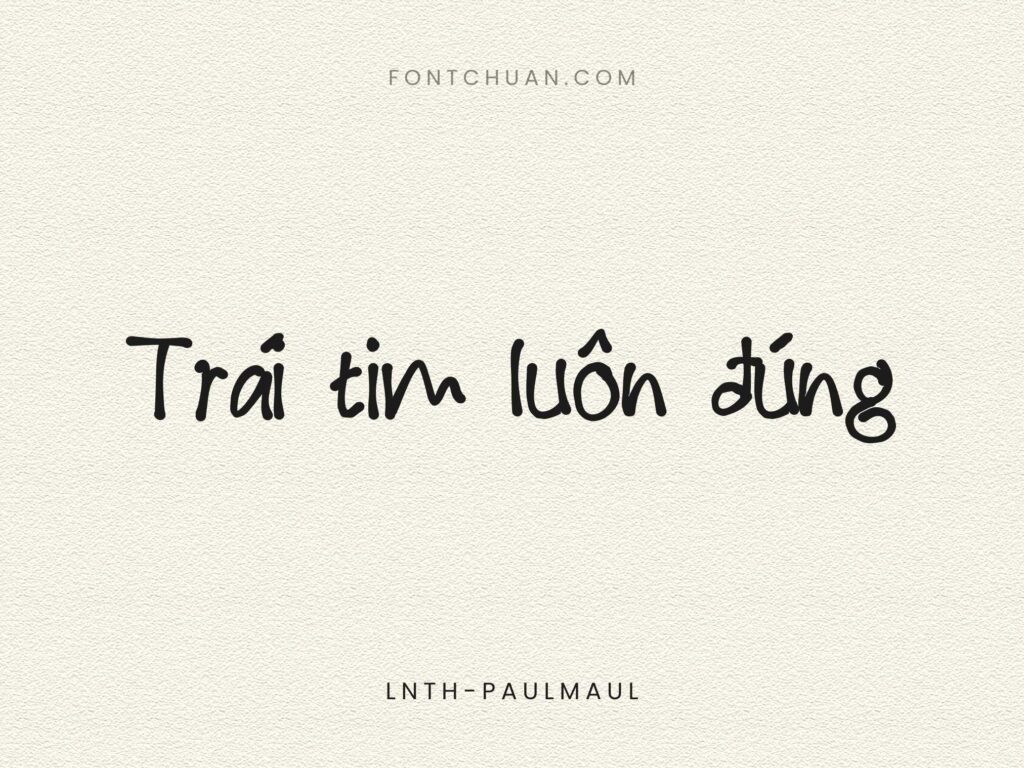
Font LNTH Paulmaul Việt Hóa
Tác giả Font: Exclamachine Type Foundry
Font PaulMaul là một kiểu chữ mang phong cách vui nhộn, pha trộn giữa nét viết tay và chữ in hoa cách điệu. Với thiết kế đậm chất sáng tạo, các ký tự có độ cong mềm mại, tạo ra cảm giác gần gũi, trẻ trung nhưng vẫn đầy cá tính. PaulMaul là lựa chọn lý tưởng cho các thiết kế poster, bao bì sản phẩm, tiêu đề hoặc các dự án mang phong cách hiện đại và phá cách
Phiên bản này đã được Việt hóa bởi LNTH, hỗ trợ đầy đủ tiếng Việt cùng hơn 50 ngôn ngữ khác, giúp người dùng dễ dàng ứng dụng trong thiết kế quốc tế. Font PaulMaul được các thành viên Font Chuẩn sưu tầm và đăng tải nhằm mang đến một kiểu chữ độc đáo, phù hợp với các thiết kế sáng tạo và nổi bật
Về đặc điểm thiết kế, PaulMaul có các đường nét dày dặn, cấu trúc chữ đơn giản nhưng vẫn mang hơi hướng thủ công. Kiểu chữ này rất phù hợp để sử dụng trong typography nghệ thuật, tiêu đề quảng cáo, thiết kế nhãn dán hoặc các ấn phẩm truyền thông sáng tạo
Font PaulMaul được ứng dụng rộng rãi trong các sự kiện như lễ hội, sinh nhật hoặc các thiết kế mang phong cách vui tươi, năng động. Nó phù hợp với nhiều ngành nghề như quảng cáo, giáo dục, bất động sản, công nghệ